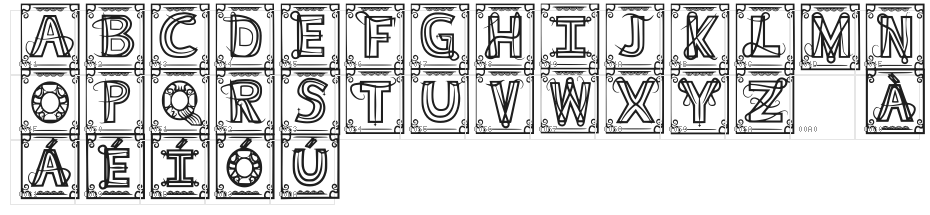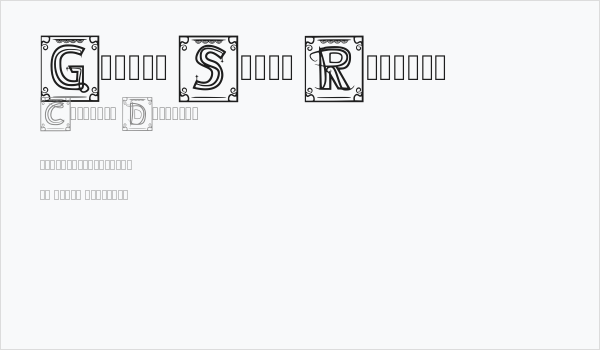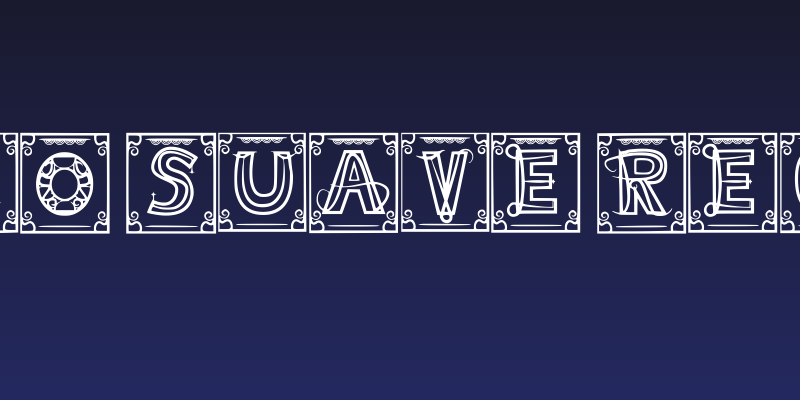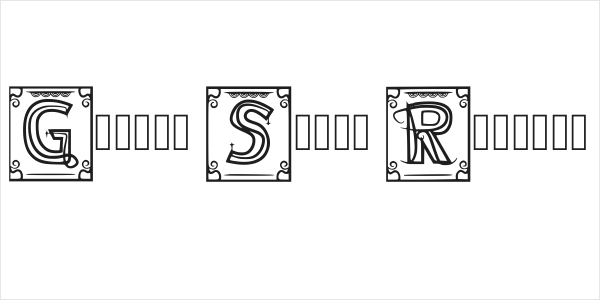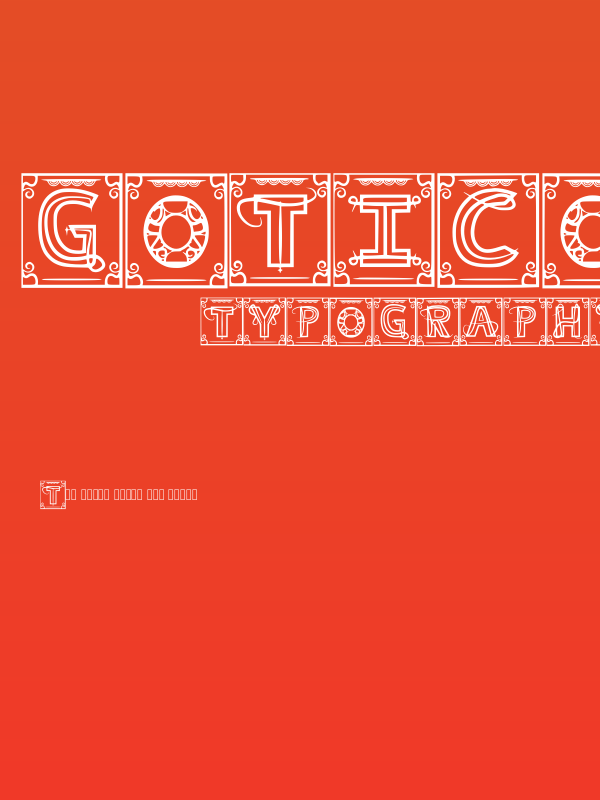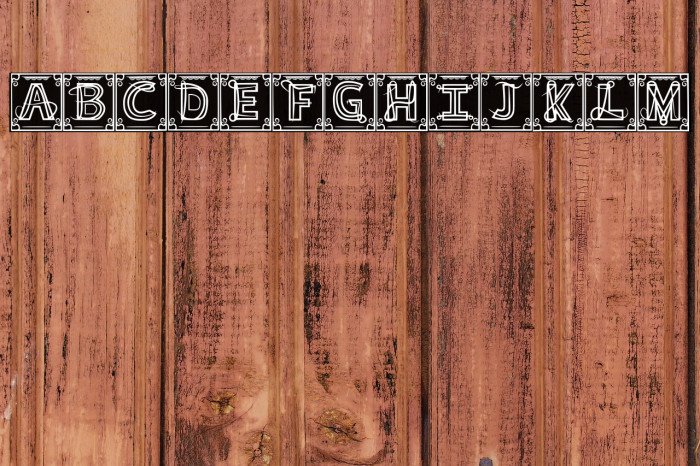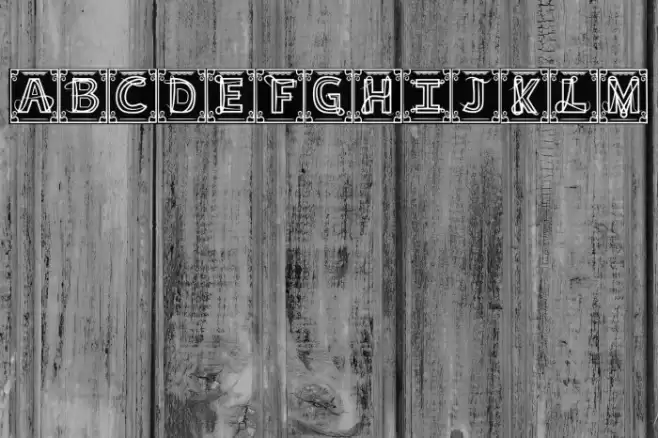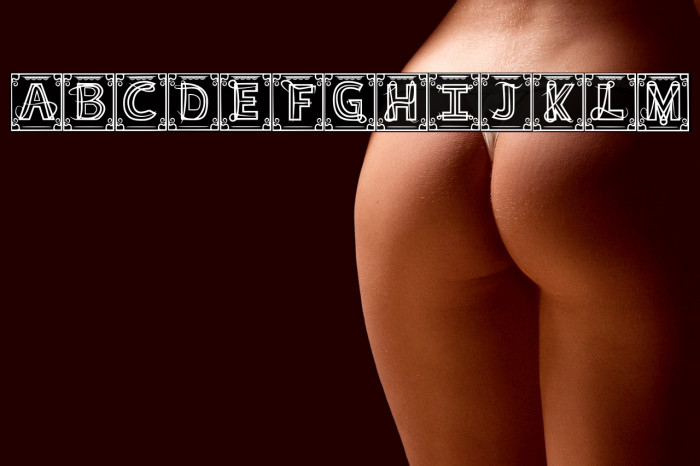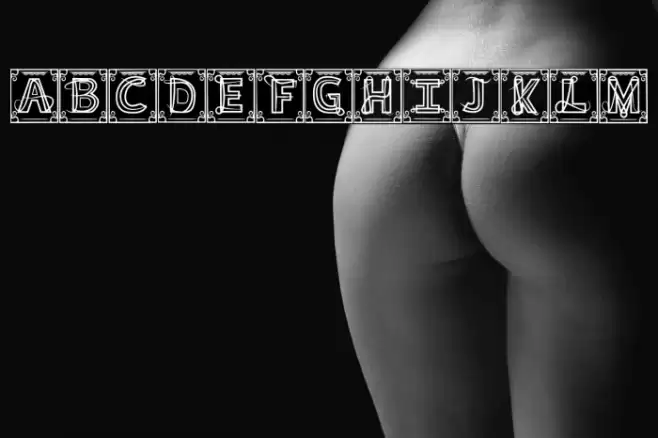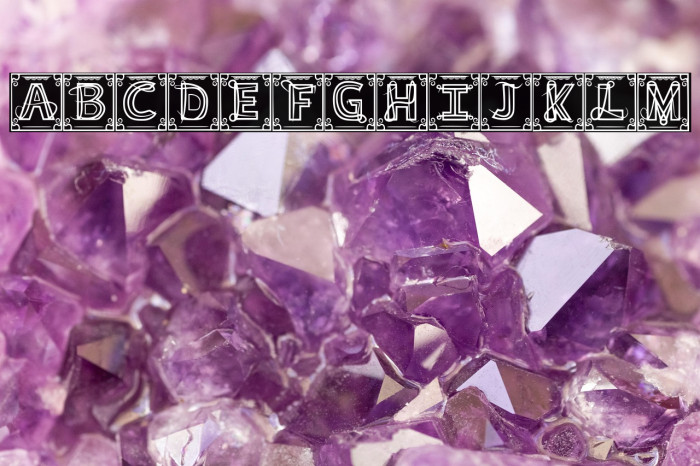
Gotico Suave Regular Font
| おすすめプロジェクト | Ideal for use in vintage-themed posters, book covers, or any design requiring a medieval or fantasy aesthetic. |